요즘 브랜드들이 산세리프 폰트를 선호하는 이유
산세리프 폰트의 역사와 유행 이유, 주의점까지
여러분들은 요즘 어떤 폰트를 자주 보고 계시나요? ✍️ 우리 일상 속에선 무심코 스쳐 지나가는 많은 것들엔 폰트가 자리를 잡고 있습니다. 그리고 이 폰트들엔 더 나은 경험을 위해 디자이너들의 섬세한 고민이 담겨있는데요. 단순 보기에 예쁜 것을 넘어, 더 나은 사용자 경험을 위해 치밀하게 기획된, 타이포그래피 디자인의 현재와 미래를 모노타입이 소개합니다.
여러분들은 산세리프 폰트를 아시나요? 산세리프 폰트란 글자 획의 끝에 돌출된 부분인 ‘세리프’가 없는 글자들을 말하는데요. 사실 산세리프 폰트가 무엇인지 잘 모르신다고 하시는 분들도 막상 산세리프 폰트 예시들을 보게 된다면 언젠가 한 번쯤 봤던 것 같은, 익숙함을 느낄 수 있으실 겁니다.
오늘날 산세리프 폰트에 대한 인기는 대단합니다. 실제 모노타입이 작년에 발표한 ‘2024 디자이너들이 사랑하는 폰트 탑10‘ 목록에서도 1위부터 5위까지 모두 산세리프 폰트가 포진해 있을 정도로 전 세계 많은 브랜드와 디자이너들이 산세리프 폰트를 사용하고 있습니다.
하지만 산세리프 폰트가 1900년대 초에 처음 등장했을 때, 단순한 유행이 아니었습니다. 시간이 지나면서 많은 브랜드가 선택하는 기본 스타일로 자리 잡았죠. 그렇다면 왜 이렇게 인기 있는 걸까요? 그리고 당신의 브랜드에는 어떤 폰트가 어울릴까요?
글로벌 폰트 및 폰트 기술 전문 기업 모노타입(Monotype)이 많은 브랜드 사이에서 산세리프 폰트가 기본 스타일로 자리잡은 이유와 함께 산세리프 폰트의 역사, 산세리프 폰트 유행 열풍에 주의해야 할 점까지 짚어보도록 하겠습니다.
산세리프 폰트의 역사
산세리프 폰트는 1816년, 윌리엄 캐슬론 4세(William Caslon IV)가 처음 만들었지만, 당시엔 큰 인기를 얻지 못했습니다. 사람들은 전통적인 글꼴을 더 선호했기 때문이죠. 하지만 20세기 초, 모더니즘이 등장하면서 상황이 달라졌습니다.
모더니즘은 “디자인은 실용적이어야 한다”라는 철학을 바탕으로 복잡한 장식 대신 단순하고 기능적인 스타일을 강조했습니다. 이에 따라 깨끗하고 구조적인 느낌을 주는 산세리프 폰트가 주목받기 시작했죠. 특히 1920년대부터 1970년대까지 ‘푸투라(Futura)’, ‘헬베티카(Helvetica)’, ‘유니버스(Univers)’, ‘프루티거(Frutiger)’ 같은 유명한 산세리프 폰트들이 등장하며 널리 쓰이게 됐습니다.
이후 기술이 발전하면서 항공우주, 의학, 생명공학 같은 미래지향적인 산업들은 산세리프 폰트를 더욱 빠르게 받아들였습니다. 깔끔하고 현대적인 이미지가 혁신적인 느낌을 주었기 때문인데요. 이후 컴퓨터와 디지털 화면이 보편화되면서 산세리프의 인기는 더욱 높아졌습니다. 초기 컴퓨터 화면은 해상도가 낮아 세리프보다 산세리프가 더 읽기 쉬웠기 때문이죠.
이것이 오늘날 디스플레이 기술이 발전했음에도 불구하고, 산세리프 폰트가 여전히 가장 인기 있는 폰트 중 하나인 이유입니다. 실제 여전히 산세리프는 브랜드 로고, 웹사이트, 앱 디자인 등에서 널리 사용되며 현대적이고 세련된 느낌을 주는 대표적인 선택지로 남아있습니다.
오늘날의 산세리프 폰트
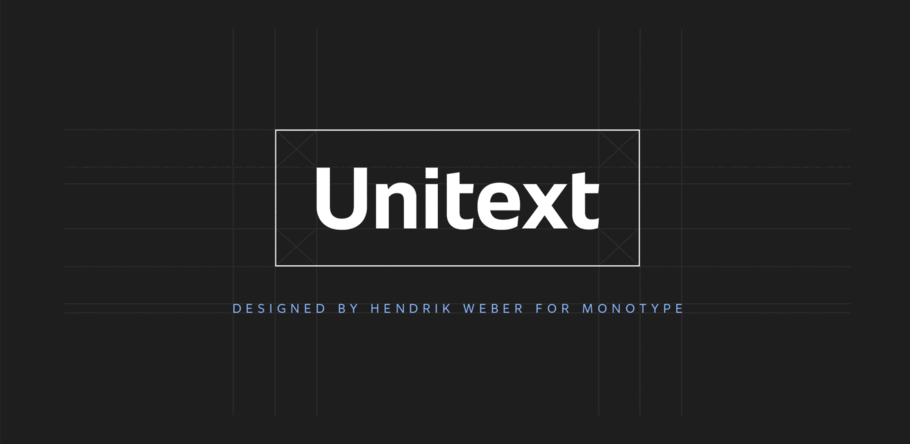
오늘날 브랜드들은 짧은 시간 안에 소비자의 관심을 끌고, 메시지를 쉽게 전달해야 합니다. 그리고 정보가 넘쳐나는 시대에는 복잡한 디자인보다 단순하고 직관적인 표현이 더 효과적이죠. 이런 이유로, 깔끔하고 읽기 쉬운 산세리프 폰트는 오늘날 많은 브랜드가 선호하고 있습니다.
특히 현대 브랜드들은 자신을 세련되고, 현대적이며, 혁신적인 이미지로 보이고 싶어 합니다. 테런스 와인지얼(Terrance Weinzierl) 모노타입 수석 타입 디자이너는 “인터넷과 소셜 미디어는 브랜드의 가치와 태도를 계속 변화시키고 있다. 소비자들의 기대가 달라지면서, 브랜드들도 자신들의 아이덴티티와 디자인을 재정비해야 한다”며 브랜드의 움직임에 대해 설명하는데요.
산세리프 폰트는 이런 브랜드들의 니즈에 맞춰 아이덴티티를 강조하거나 이미지 변화에 있어 딱 맞는 선택지입니다.
호환성과 가독성이 뛰어난 폰트
물론 단순하고 직관적인 표현이 산세리프 폰트의 모든 매력은 아닙니다. 산세리프 폰트가 인기 있는 이유는 어떤 매체에서도 잘 읽을 수 있기 때문인데요. 산세리프 폰트는 인쇄물, 웹사이트, 모바일 앱, 영상 등 다양한 환경에서 높은 가독성을 보입니다.
또한 와인지얼 디자이너는 “타깃(Target), 갭(Gap), 아메리칸 어패럴(American Apparel) 이 기업들 모두 헬베티카를 사용하지만, 각 브랜드의 카피라이팅, 이미지, 색상에 따라 완전히 다른 분위기를 연출합니다”라며 대표적인 산세리프 폰트 ‘헬베티카(Helvetica)’를 예로 들며 산세리프의 가독성과 호환성 강조합니다.
브랜드의 변화를 보여주는 도구
브랜드가 리브랜딩을 할 때도 산세리프 폰트는 중요한 역할을 합니다. 예를 들어, 글로벌 부동산 프랜차이즈 기업 리맥스(Remax)는 더 현대적인 느낌을 주기 위해 기하학적 산세리프 폰트로 변경했습니다. 노벨상 재단(Nobel Prize organization)은 더욱 신뢰감 있고 지적인 이미지를 강조하기 위해 새로운 산세리프 스타일 폰트와 색상을 도입했죠.
이에 대해 와인지얼 디자이너는 “폰트는 단순한 디자인 요소가 아닙니다. 기업이 새로운 방향을 잡거나, 리더십이 바뀌거나, 제품을 재설계할 때 폰트 변경이 그 변화를 상징할 수 있습니다”라고 설명하는데요.
이처럼, 산세리프 폰트는 단순한 유행이 아니라 브랜드가 현대적인 이미지를 유지하고, 변화하는 시장에 효과적으로 적응할 수 있도록 돕는 강력한 도구로 작용할 수 있습니다.
모든 브랜드에 어울리는건 아니다
하지만 산세리프 폰트가 인기 있다고 해서 모든 브랜드에 어울리는 것은 아닙니다. 물론, 경쟁사들이 산세리프 폰트를 사용하니까 우리도 따라가야 한다는 압박을 느낄 수도 있죠. 하지만 폰트 선택에서 가장 중요한 것은 브랜드의 정체성과 어울리는지 여부입니다.
실제 와인지얼 디자이너는 “많은 브랜드가 ‘다들 이 폰트를 쓰니까 우리도 써야 한다’라고 생각하지만, 그게 꼭 맞는 선택은 아닙니다”라고 말하면서 무분별한 산세리프 폰트 사용을 경고하는데요.
그렇다면 브랜드 폰트를 선택할 때 어떤 점을 고려해야 할까요? 와인지얼 디자이너는 먼저 브랜드의 성격과 가치를 깊이 이해해야 한다고 강조합니다. 단순히 트렌드를 따라가기보다는, 브랜드의 특징을 이해하고, 브랜드의 아이덴티티를 잘 표현할 수 있는 폰트를 선택하는 것이 더 중요하다는 이야기죠.
브랜드만의 개성을 살릴 수 있는 폰트가 핵심
산세리프 폰트는 현대적이고 깔끔한 느낌을 주지만, 모두가 비슷한 디자인을 선택하면 브랜드가 개성을 잃을 수 있습니다. 트렌드를 따르는 것도 의미가 있지만, 결국 중요한 것은 우리 브랜드만의 차별점을 어떻게 드러내느냐입니다.
물론 산세리프 폰트는 시대의 변화와 흐름을 반영할 수 있다는 장점이 있습니다. 그러나 더 본질적인 것은 폰트 선택이 브랜드의 개성을 살리면서 동시에 최신 디자인 경향과 균형을 이루는지 여부입니다. 따라서 단순히 유행을 좇기보다, 브랜드만의 정체성을 유지할 수 있는 방향으로 선택하는 것이 핵심입니다.
전용 폰트를 사용하는 것도 좋은 방법이 될 수 있습니다. 브랜드만의 독창적인 폰트를 사용하면, 흔한 폰트를 선택하는 것보다 더 강한 개성과 정체성을 구축할 수 있기 때문입니다.
산세리프의 다음은?
산세리프 폰트의 미래는 정확히 예측할 수 없지만, 기술 발전이 폰트 디자인에 큰 영향을 미칠 것이라는 점은 분명합니다. 와인지얼 디자이너는 앞으로 폰트 소프트웨어가 더 발전하면서, 산세리프 폰트가 다양한 환경에 더욱 유연하게 적응할 수 있을 것이라고 전망합니다.
특히 그는 미래에는 가상 현실(VR)이나 증강 현실(AR) 환경에서 거리와 각도에 따라 별도 설정 없이 스스로 자동으로 크기와 두께를 조정하는 폰트가 나올 수도 있으며, 심지어 움직임이나 애니메이션에 맞춰 자연스럽게 변화하는 폰트가 개발될 가능성이 있다고 말합니다.
앞으로 브랜드가 성공하려면 자신만의 개성을 유지하면서도 새로운 기술과 변화에 유연하게 적응하는 것이 중요합니다. 소비자 경험이 계속 진화하는 만큼, 폰트도 단순한 디자인 요소를 넘어 브랜드의 정체성을 표현하는 중요한 도구로 발전해 나갈 것입니다.